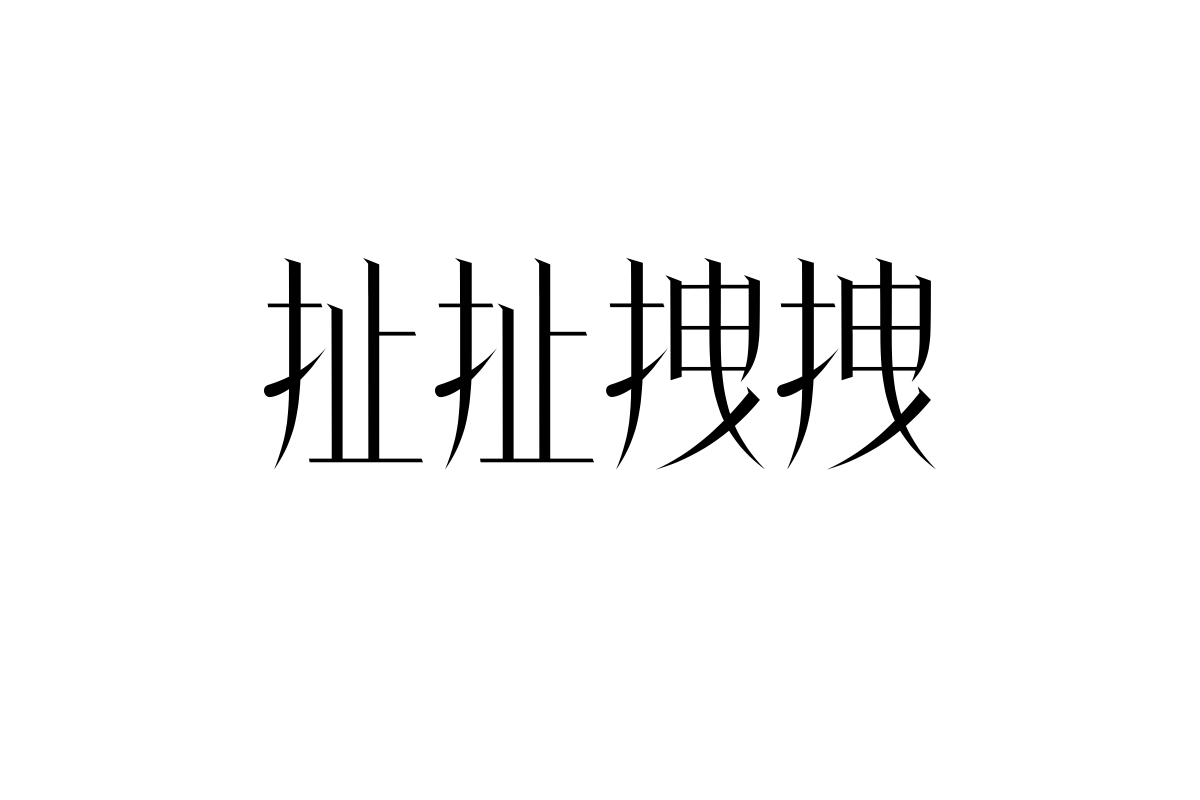
上首纤云体是一种书法字体,它的字形结构独特,笔画流畅自然。这种字体的特点是笔画细长而有力,线条优美而富有弹性,给人一种优雅、柔美的感觉。上首纤云体的笔画粗细变化较大,既有粗犷的线条,也有细腻的笔触,使得整款字体既有力量感,又不失灵动性。
上首纤云体在书法作品中经常被使用,它能够很好地表达出作者的情感和意境。这种字体适合用于书写诗词、对联、书法作品等,能够展现出一种独特的艺术魅力。